Mit dem Handbuch Handlettering erschien im Schweizer Haupt Verlag ein weiteres Buch zum Trendthema Lettering. Die Autorin Chris Campe ist ausgebildete Buchhändlerin und hat Kommunikationsdesign (in Hamburg und Paris) und Kulturwissenschaften (in Chicago) studiert. Seit 2014 hat sie sich mit ihrem Büro All Things Letters auf Schrift und Typografie spezialisiert.
Ihr Wissen zum Thema und ihre arbeitstechnische Herangehensweise werden im vorliegenden, 160-seitigen Buch dargeboten.
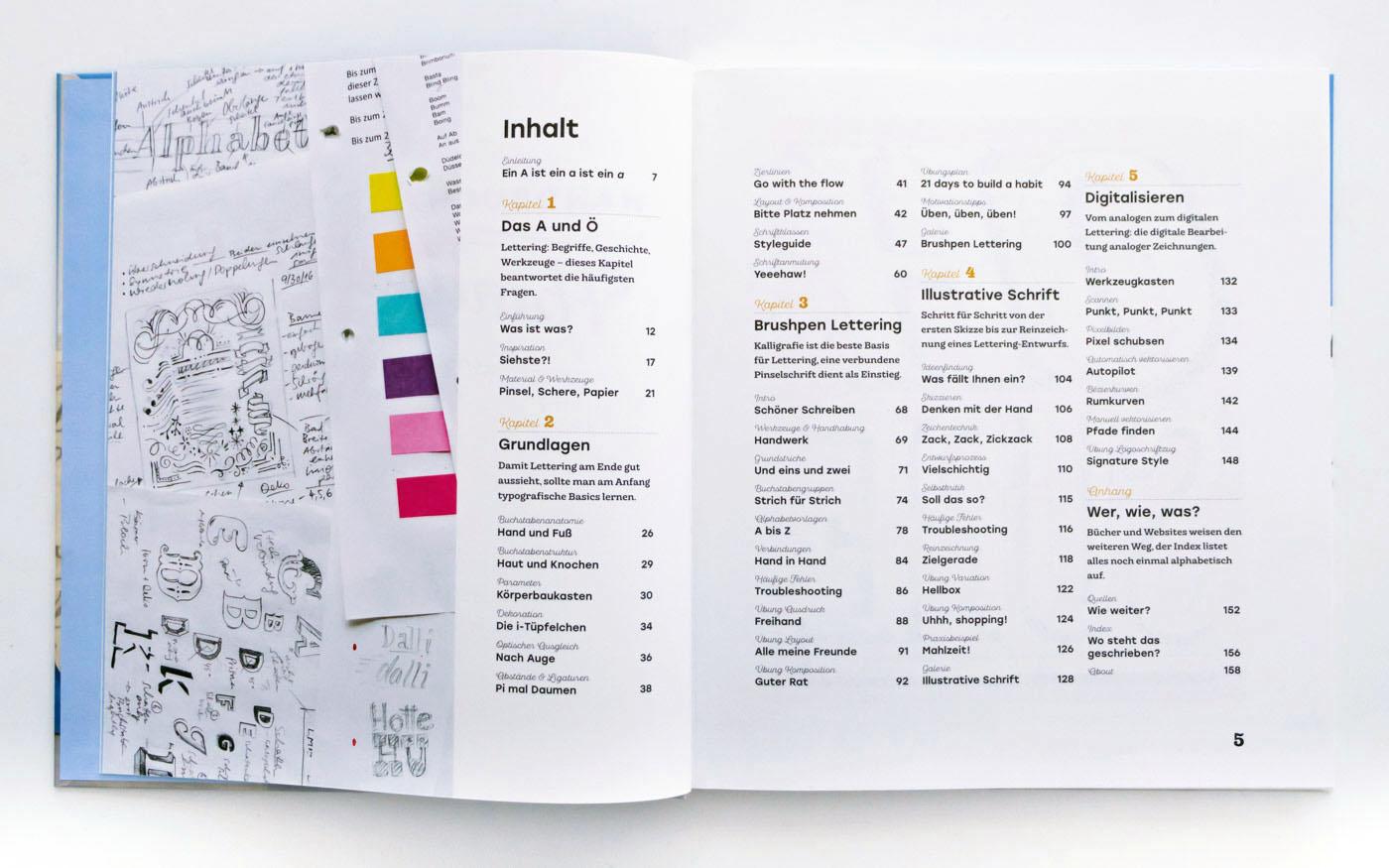
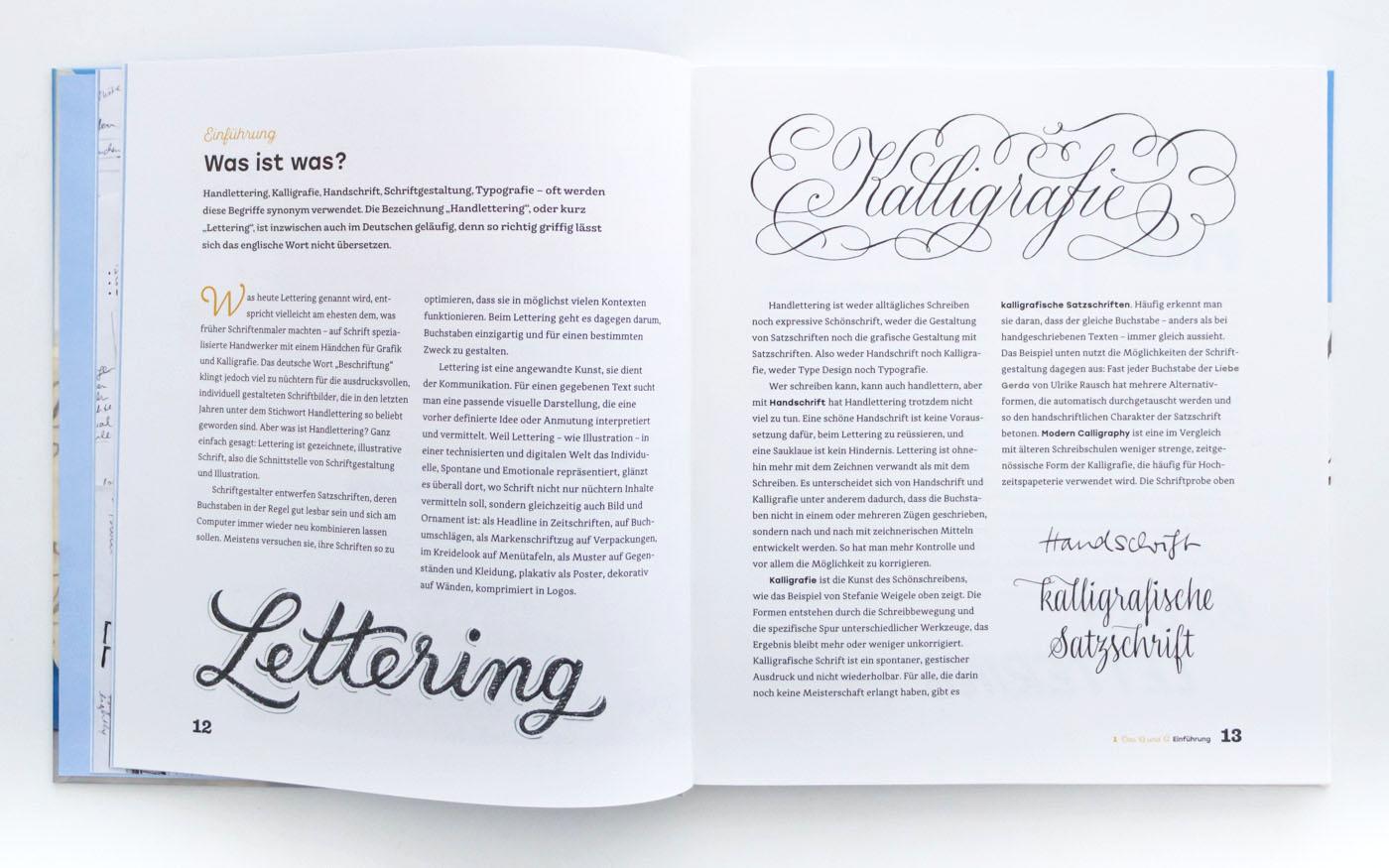
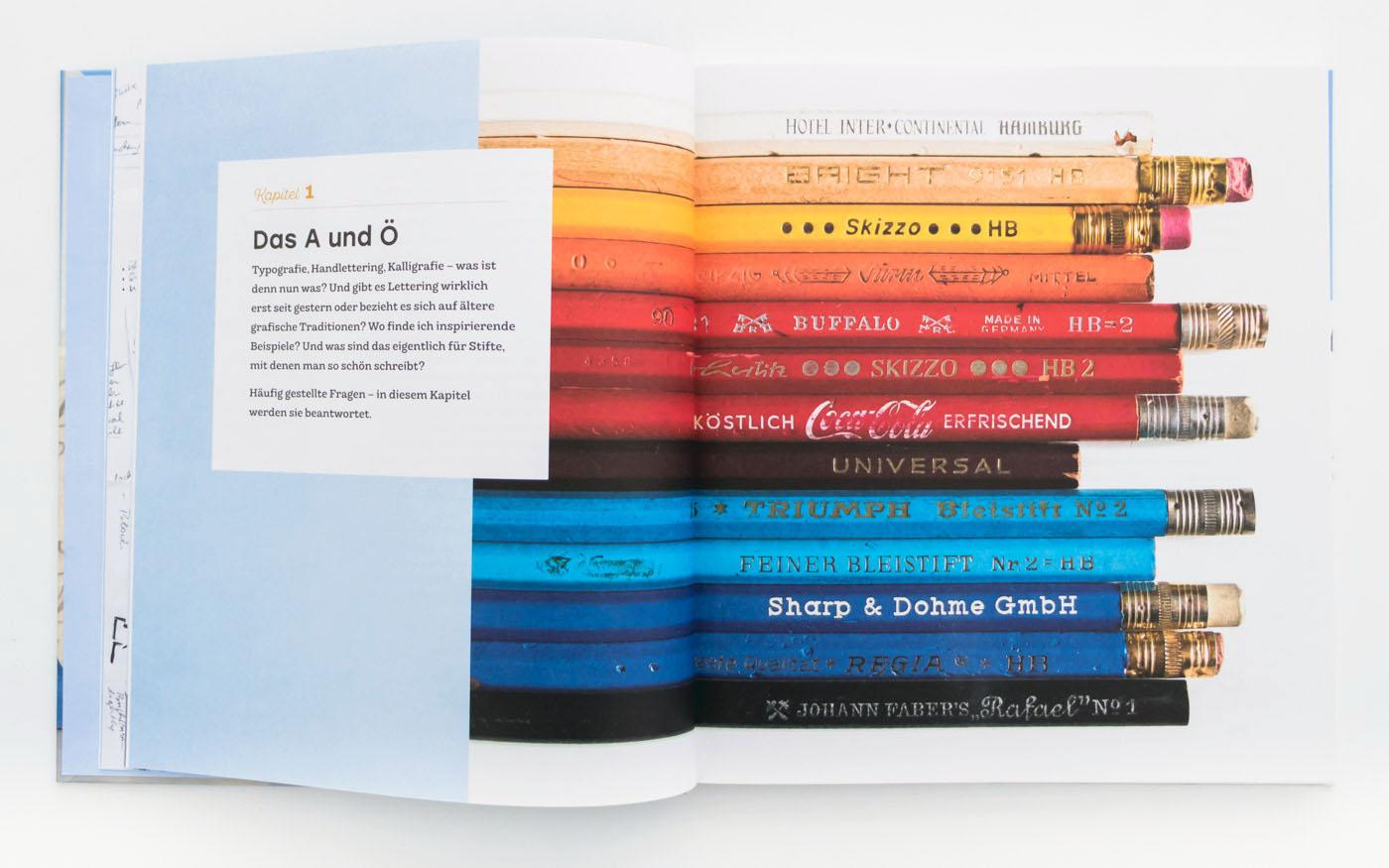
Die ersten 60 Seiten widmen sich ausführlich den Grundlagen: Begriffserklärungen, Lettering-Materialien, Schriftstile, typografisches Einmaleins usw.
Als Anleitung zum Lettering folgen zwei Hauptkapitel: Brushpen Lettering als geschriebene Pinselschrift wird über circa 30 Seiten erklärt. Im folgenden Kapitel geht es um die tatsächlich gezeichnete Schrift. Neben der Zeichentechnik wird hier auch Ausdruck und Seitenaufbau viel Raum gegeben.
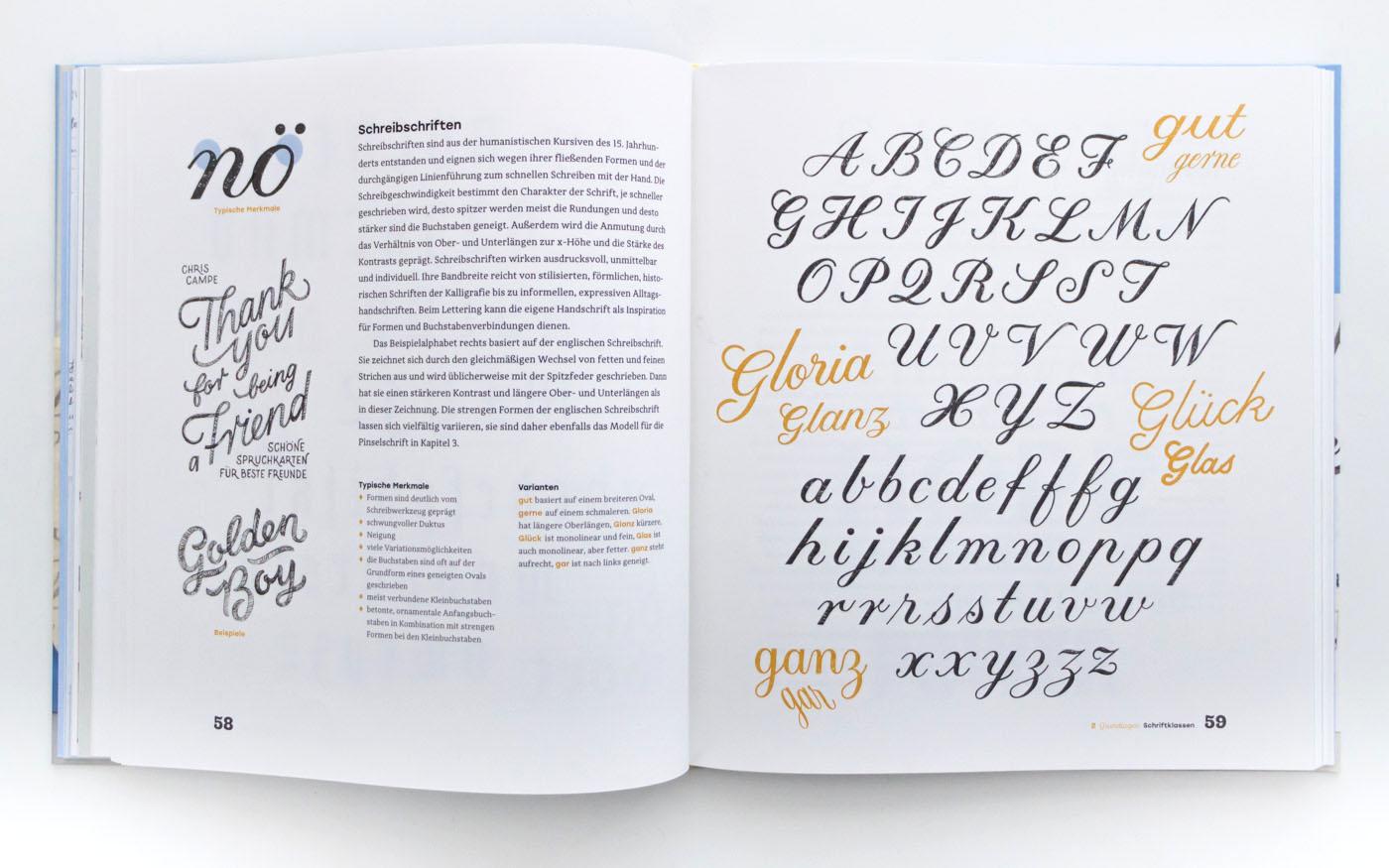
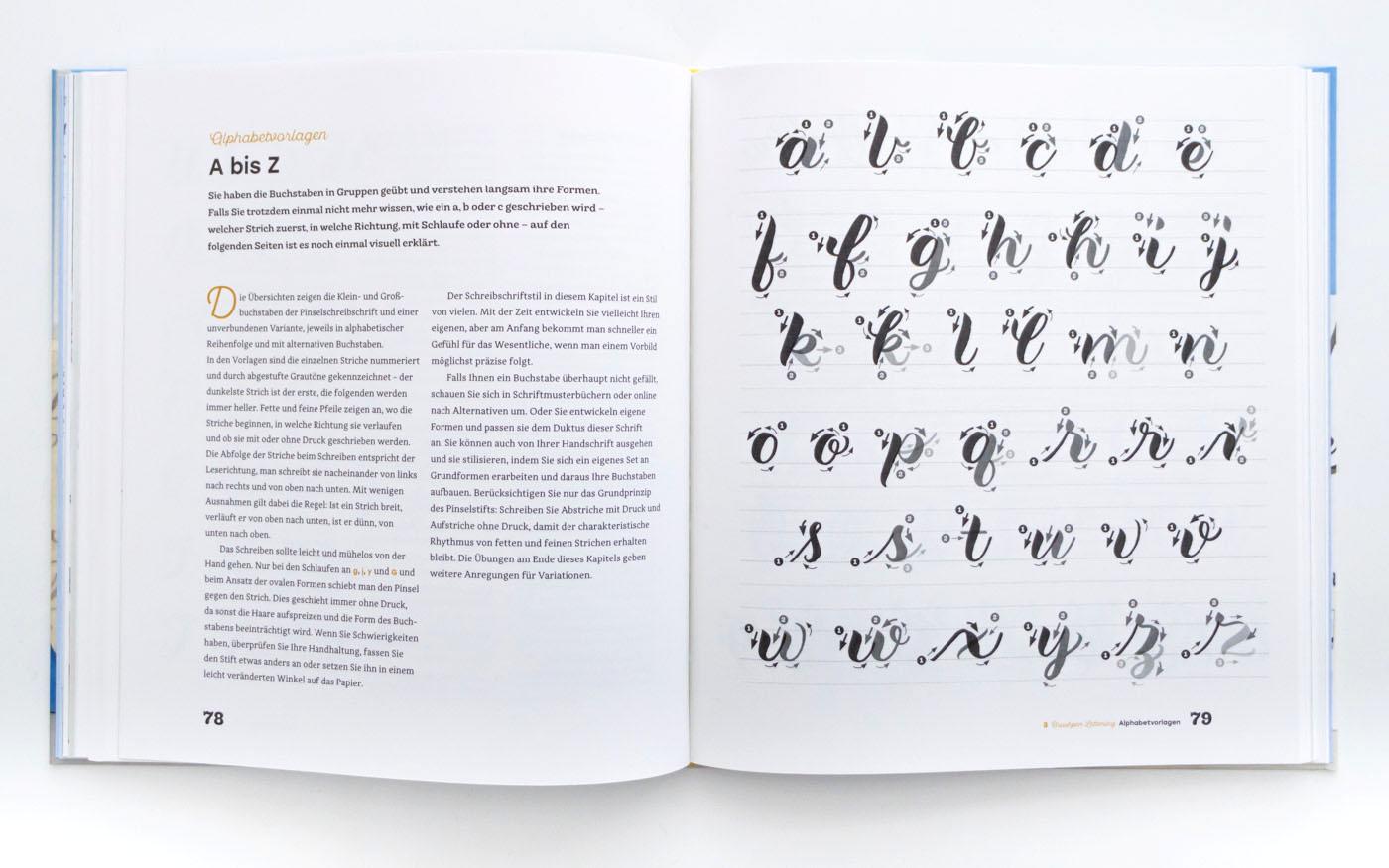
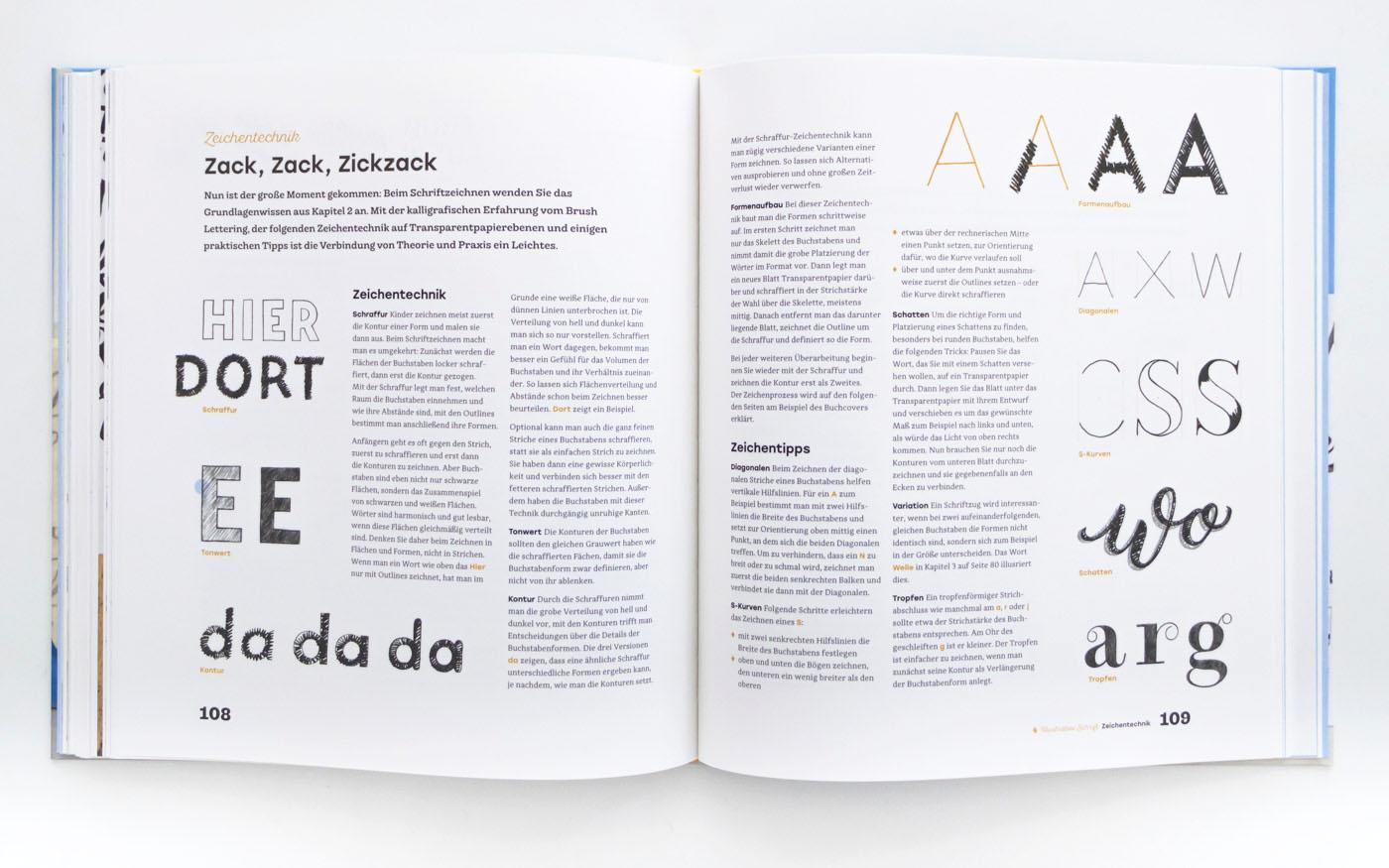
Das letzte Kapitel widmen sich dem Digitalisieren der analogen Ergebnisse. Ein Aspekt, der insbesondere für kommerzielle Lettering-Anwendungen (Logos, Buchcover usw.) natürlich auch eine wichtige Rolle spielt.
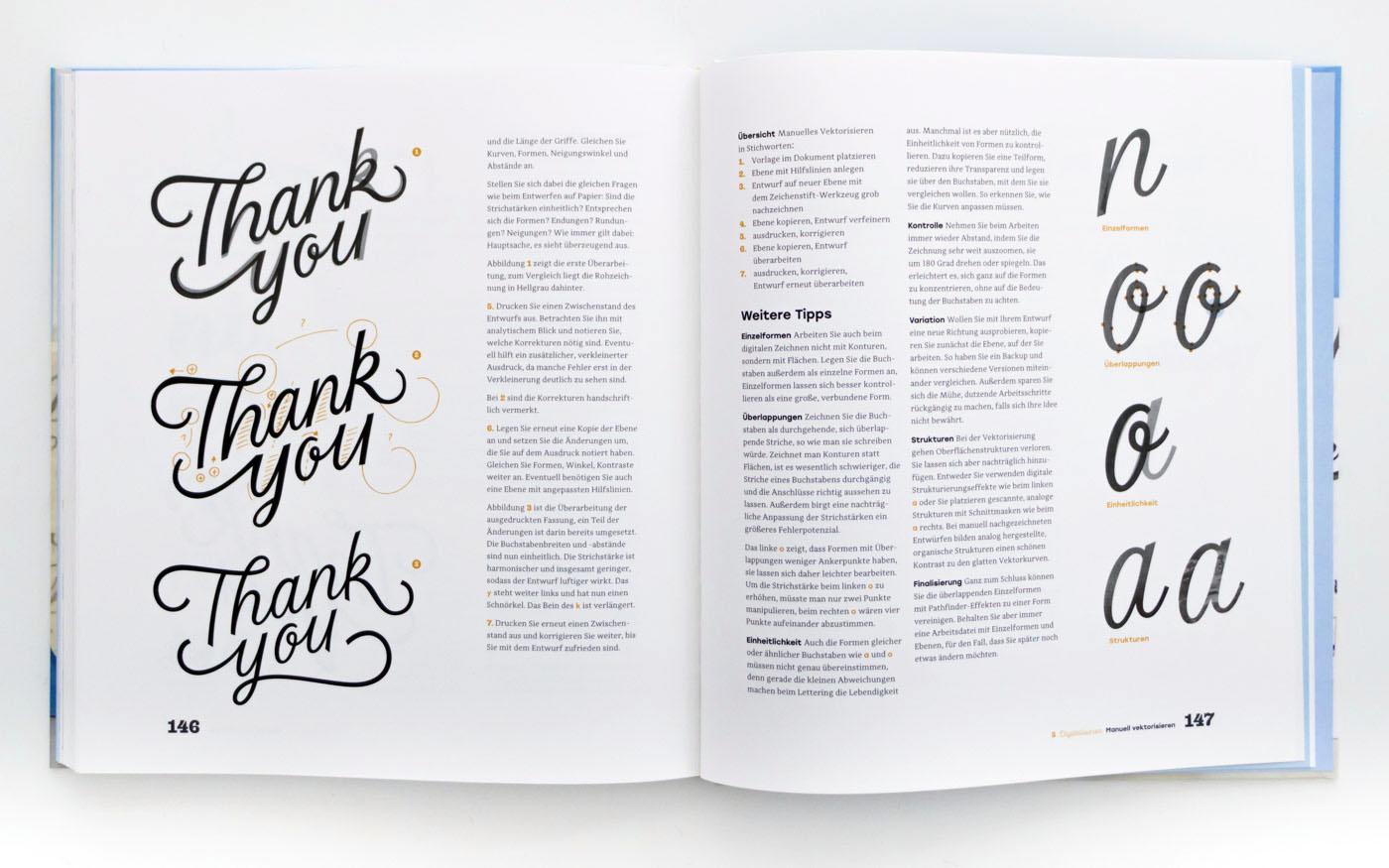
Das reich illustrierte und ansprechend gestaltete Buch baut auf fundiertes Wissen zum Thema Schrift auf. Man kann das Buch also auch Fachleuten wie Grafikdesignern und Illustratoren, die in das Thema Lettering einsteigen wollen, bedenkenlos empfehlen. Wie auch Lust auf Lettering von Martina Flor, gibt das Handbuch Handlettering einen Überblick über die Thematik. Grundlagen, Materialen und Arbeitsweisen werden fundiert und im Zusammenhang erläutert. Doch das Handwerk des Lettering-Profis kann man sich freilich nicht mit einzelnen Büchern anlesen. Hier heißt es letztlich üben, üben, üben. Mehr als gutes Überblickswissen sollte man also nicht erwarten. Auch ist das Buch bewusst nicht als Übungsbuch angelegt. So ist man nach der Lektüre des Buches ohne begleitende Kurse dann in der Umsetzung des Schreibtrainings doch wieder auf sich allein gestellt. Eventuell könnten hier in Zukunft noch Schreibvorlagen zum Herunterladen nachgelegt werden.
- Handbuch Handlettering. Eigene Buchstaben & illustrative Schrift gestalten
- Autor: Chris Campe